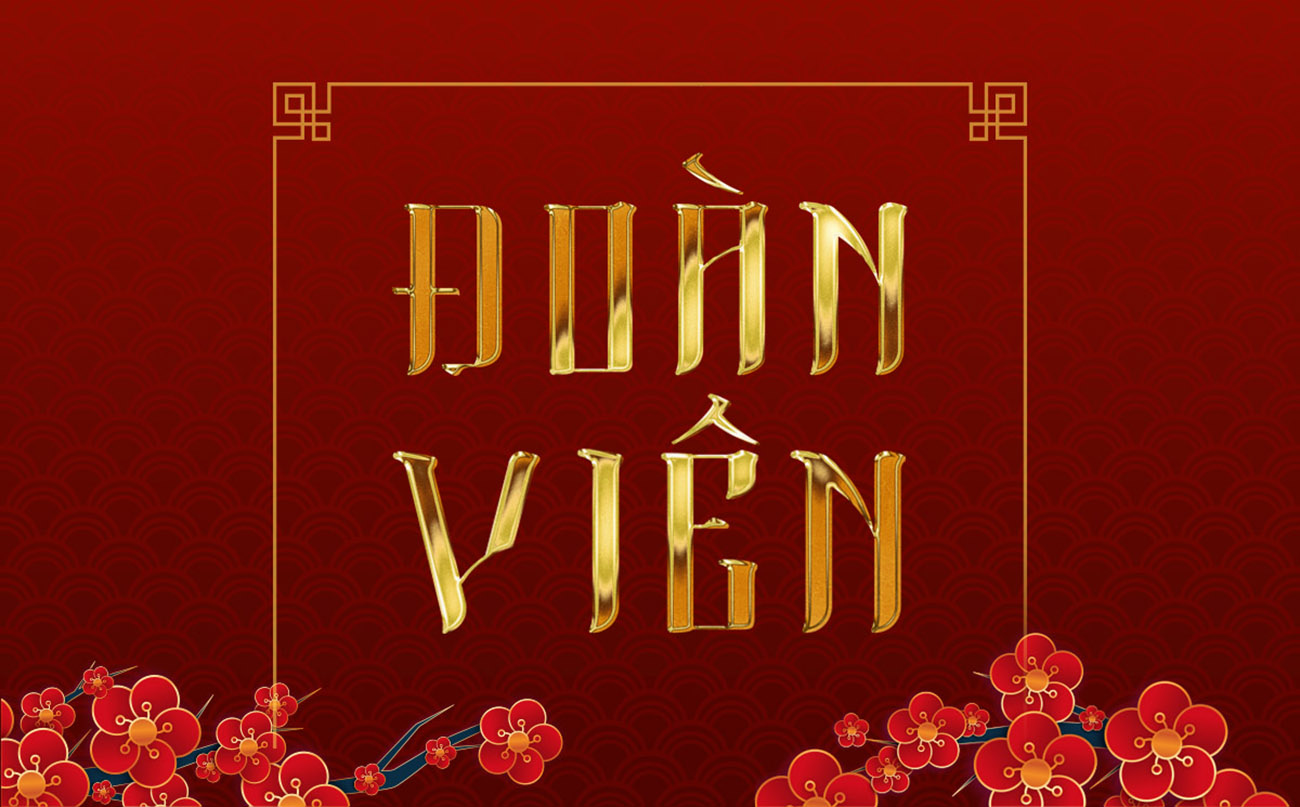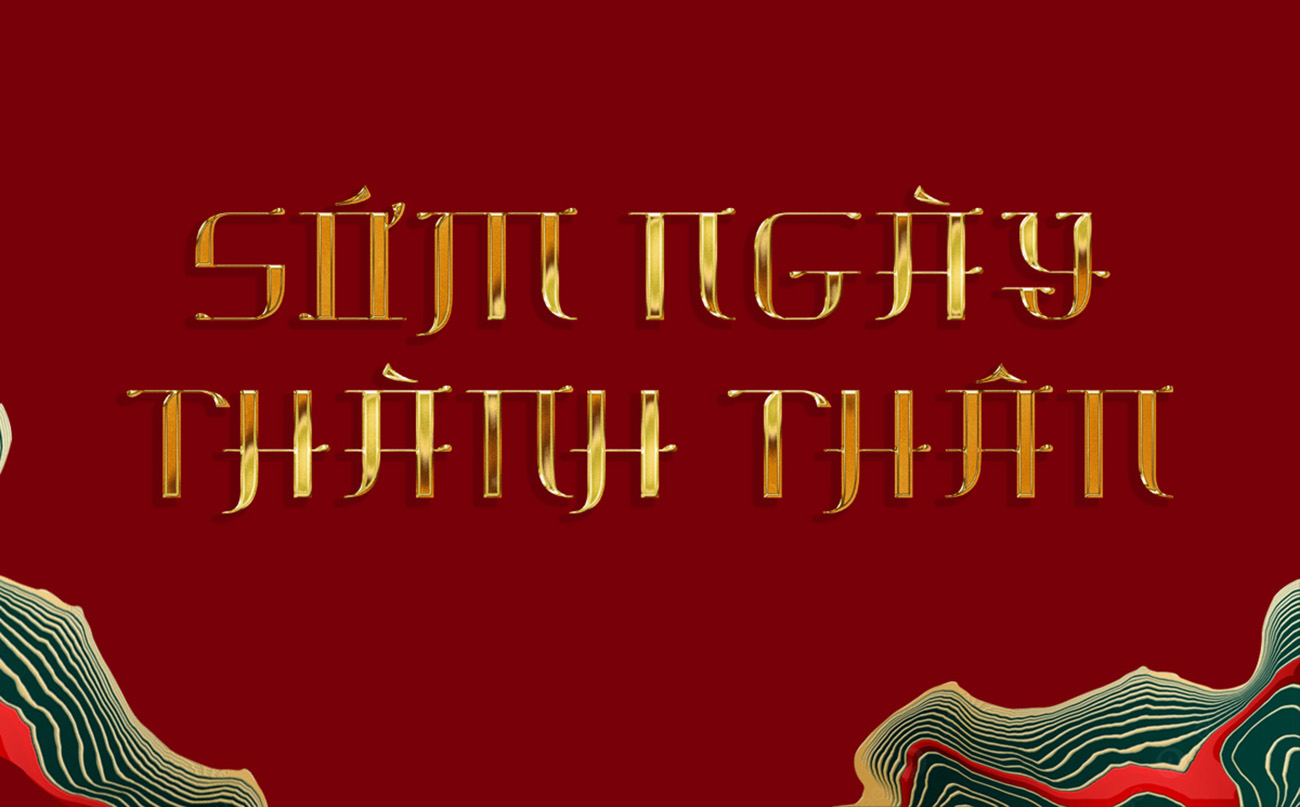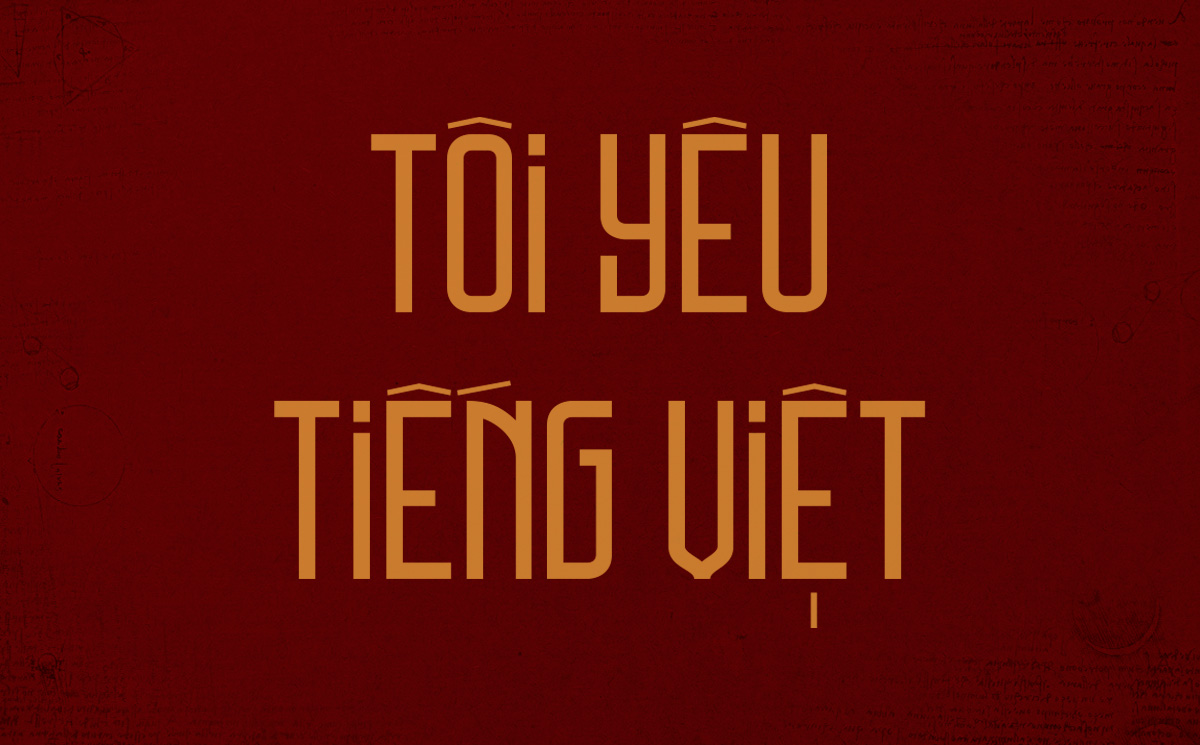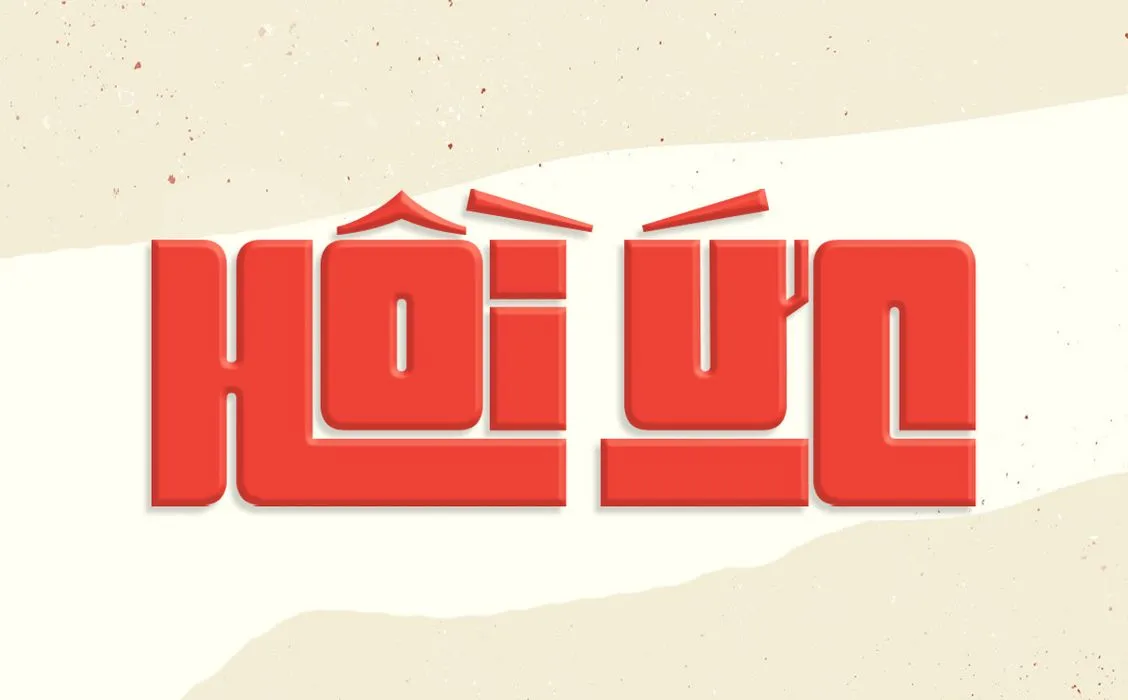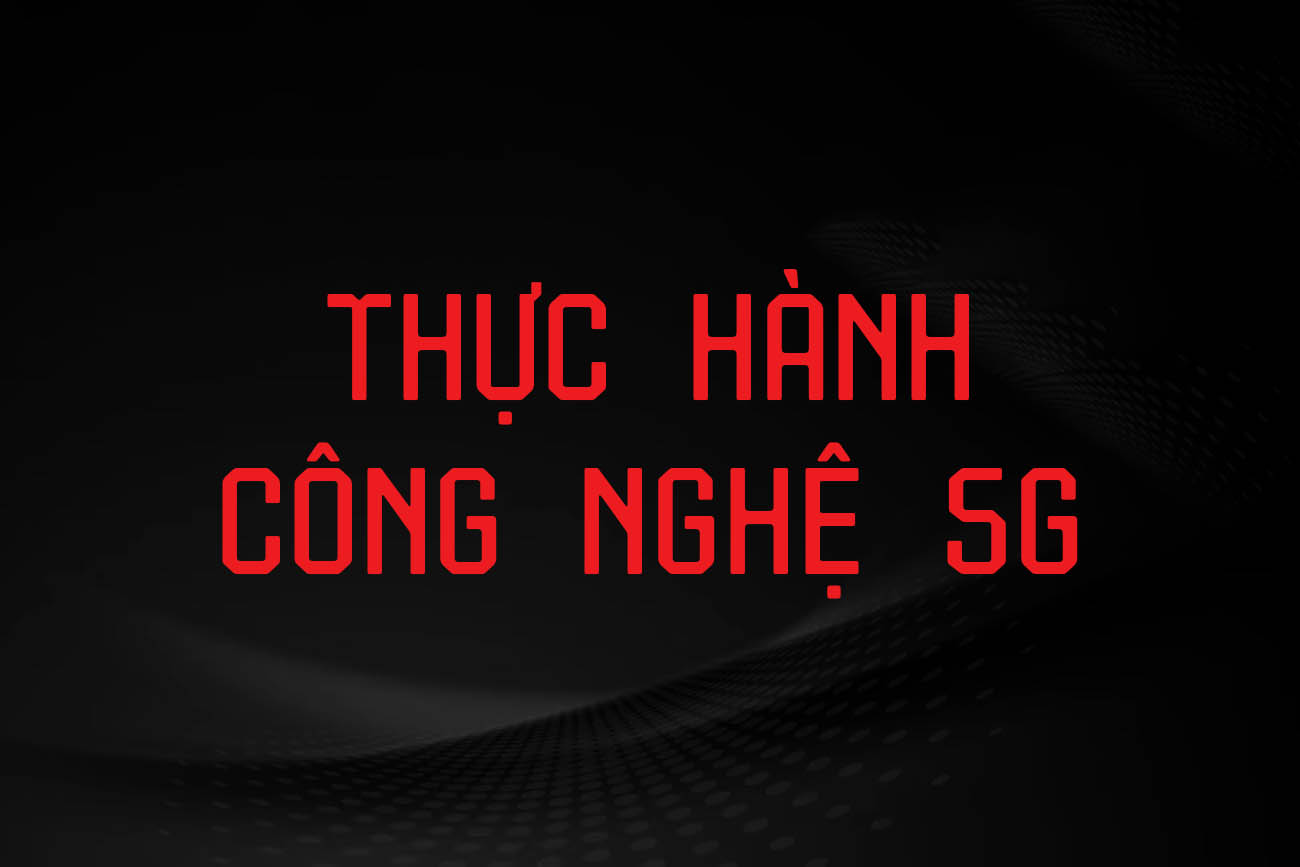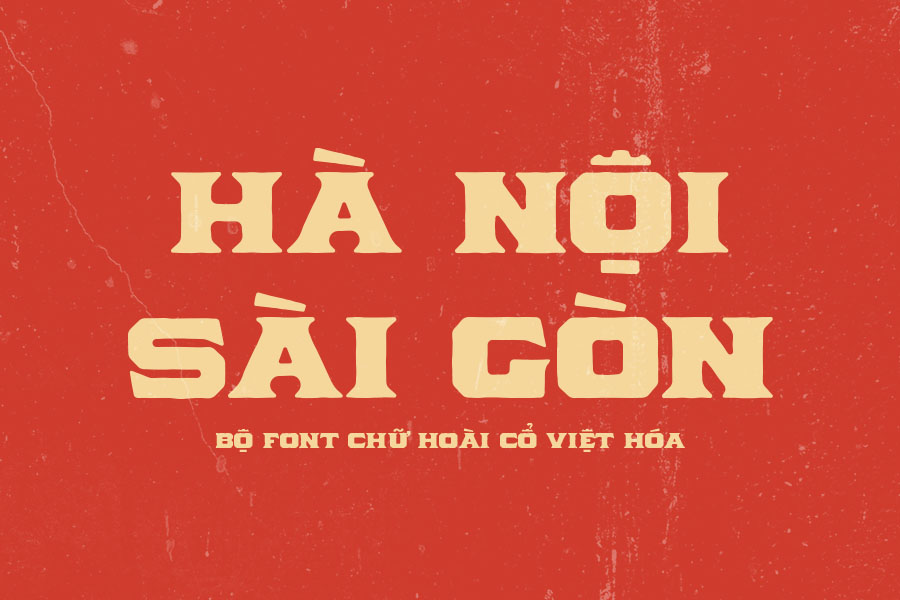
Top 12+ Font Chữ Vuông Việt Hóa Cho Thiết Kế Xưa Cũ
Khám phá bộ font chữ vuông Việt hóa đẹp nhất 2025 – vuông vức, hiện đại, rõ ràng, tải miễn phí tại Fontdep.vn.
Trong thiết kế, font chữ không chỉ đơn thuần là công cụ trình bày – mà còn là mảnh ghép văn hóa, phản ánh tinh thần của từng giai đoạn lịch sử. Ở Việt Nam, những font chữ vuông gợi nhớ biển hiệu phố xưa, áp phích cổ động hay ấn phẩm truyền thống luôn mang đến cảm giác gần gũi và đầy hoài niệm. Nếu bạn đang tìm kiếm phong cách xưa cũ, trang trọng và mang đậm dấu ấn văn hóa Việt, thì font chữ vuông chính là lựa chọn lý tưởng.
Bài viết này từ Fontdep.vn sẽ giới thiệu đến bạn bộ sưu tập font chữ vuông Việt hóa đẹp nhất 2025, mang hơi thở cổ điển, hoài niệm và gắn liền với bản sắc truyền thống.
Font chữ vuông là gì?
Font chữ vuông là kiểu chữ được thiết kế với hình dáng cân đối, gọn gàng, các nét thẳng và góc cạnh rõ ràng. Khác với những font hiện đại, font vuông mang đậm tinh thần xưa cũ và hoài cổ, thường gợi nhớ đến biển hiệu tiệm buôn, bảng quảng cáo, poster cổ động hay các ấn phẩm văn hóa từ thế kỷ trước.
Điểm đặc trưng của font vuông là sự chắc chắn, trang nghiêm và rõ ràng, tạo cảm giác bền bỉ, vững chãi – phù hợp để tái hiện không khí truyền thống, tôn vinh giá trị lịch sử và văn hóa Việt Nam. Chính nhờ đó, font chữ vuông luôn được các nhà thiết kế lựa chọn trong những dự án cần sự cổ kính, trang trọng hoặc gợi nhớ về ký ức thị giác của một thời đã qua.
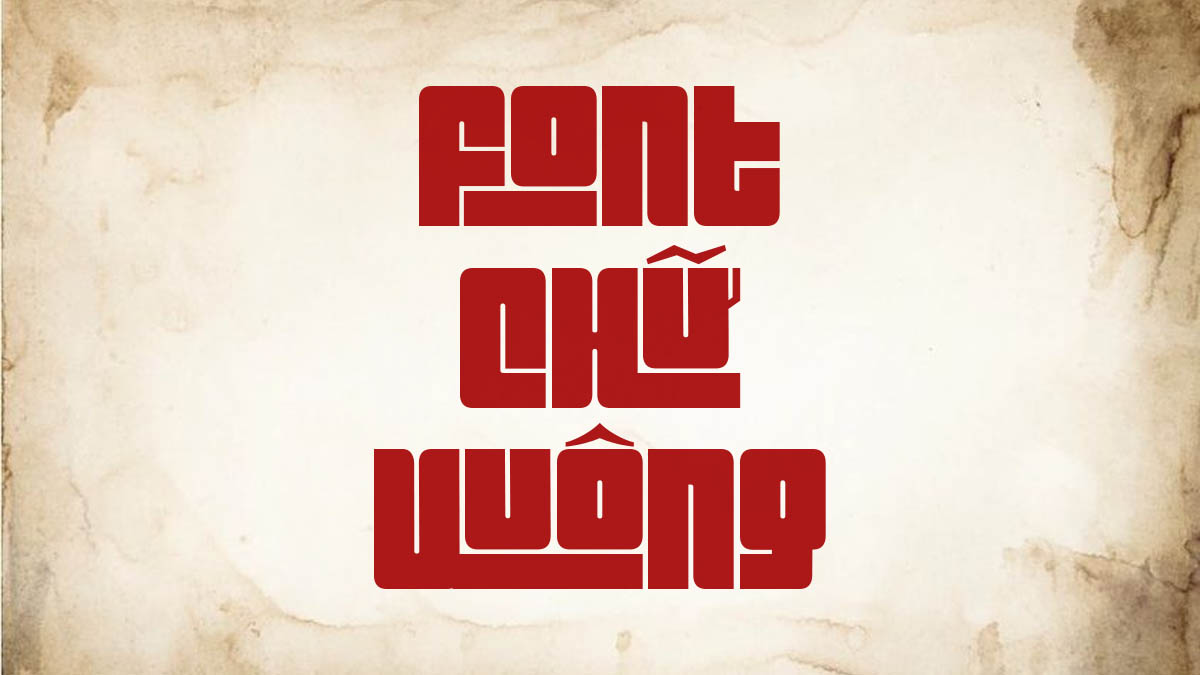
Top Font Chữ Vuông Việt Hóa Đẹp Nhất 2025
Dưới đây là những font chữ vuông vắn đẹp, đã được Việt hóa đầy đủ và rất đáng thử trong các dự án thiết kế hiện đại:
1. TH Lichsu 3 – Cổ điển, thanh mảnh
Font TH Lichsu 3 nổi bật với kiểu chữ kéo dài theo chiều dọc, thân chữ hẹp và phần đỉnh được xử lý sắc nét. Nét chữ mảnh nhưng không yếu, tạo nên phong cách truyền thống, nghiêm trang. Phù hợp với các thiết kế cần sự trang trọng, cổ kính và tính nghi lễ như poster Phật giáo, sự kiện văn hóa truyền thống.
2. TH Nhat Ban 1 – Thẳng đứng, trang nghiêm
Font TH Nhat Ban 1 gây ấn tượng bởi kiểu chữ cao và gầy, các nét dọc kéo dài tạo cảm giác trang trọng, uy nghi. Thiết kế vuông vức ở phần thân kết hợp với chi tiết bo nhẹ nơi chân chữ giúp font giữ được sự cân đối mà không bị thô cứng. Phần đầu nét chữ được xử lý sắc sảo gợi liên tưởng đến thẩm mỹ kiến trúc truyền thống Nhật Bản, khiến font trở nên rất riêng biệt, phù hợp trong thiết kế gắn với yếu tố văn hóa, nghệ thuật phương Đông hoặc cổ trang.
3. TH Degrad Mono – Cứng cáp, tối giản
Font TH Degrad Mono mang đặc trưng của kiểu chữ monospace với độ rộng ký tự đồng đều và các đường nét vuông gọn, dứt khoát. Mỗi chữ cái được thiết kế theo cấu trúc hình học đơn giản nhưng chắc chắn, tạo cảm giác mạnh mẽ và hiện đại. Dù không quá phức tạp trong chi tiết, font vẫn giữ được cá tính riêng nhờ cấu trúc thẳng đứng, phù hợp với thiết kế công nghệ, tiêu đề typography hoặc giao diện mang tính kỹ thuật số cao.
4. TH Lichsu 1 – Cổ kính, quyền uy
Font TH Lichsu 1 mang phong cách đậm chất hoàng gia với kiểu dáng chữ đứng cao, khối vuông vững chãi kết hợp chi tiết uốn lượn trang trí nơi đầu và chân chữ. Các nét kéo dài đầy đặn tạo cảm giác oai nghiêm, phù hợp với những chủ đề gắn liền với lịch sử, cung đình hoặc văn hóa cổ truyền. Kiểu chữ này thể hiện khí chất quyền lực nhưng không mất đi sự tinh xảo, giúp tổng thể thiết kế trở nên nổi bật và có chiều sâu văn hóa.
- Việt hóa bởi: Phạm Sơn - Admin S99, Fontdep.vn
5. TH China 1 – Hộp khối, phá cách
Font TH China 1 sở hữu cấu trúc cực kỳ đặc biệt với các ký tự hình khối vuông chắc nịch, kết hợp những nét cắt mạnh và góc cạnh kiểu cách tạo nên cảm giác như ký hiệu cổ trang được mã hóa. Mỗi chữ cái đều như một hình vẽ độc lập, nhưng khi ghép lại lại tạo thành tổng thể liền mạch và dễ nhận diện. Font gợi nhớ đến văn hóa phương Đông qua lối thiết kế giả lập, hiện đại mà vẫn đậm chất truyền thống, rất phù hợp cho các dự án cổ trang giả tưởng, phim hoạt hình hoặc poster game lịch sử.
- Việt hóa bởi: Phạm Sơn - Admin S99, Fontdep.vn
6. TH Hoaico 2 – Cổ điển, vững chãi
Font TH Hoaico 2 tái hiện rõ nét tinh thần thiết kế bảng biển và ấn phẩm truyền thông thời bao cấp với form chữ dày, chân to, đầu bo nhẹ tạo cảm giác cũ kỹ nhưng vẫn dễ nhìn. Các ký tự mang tỷ lệ vuông gần chuẩn, nét cắt khỏe khoắn, tạo nên sự chắc chắn và mạnh mẽ trong thị giác. Dù mang đậm phong cách retro Việt Nam, font vẫn rất linh hoạt khi áp dụng vào thiết kế hoài niệm như poster phim xưa, bìa sách lịch sử hoặc các dự án tôn vinh văn hóa đô thị cổ.
- Việt hóa bởi: Phạm Sơn - Admin S99, Fontdep.vn
Font chữ vuông không chỉ là lựa chọn thẩm mỹ trong thiết kế, mà còn là nhịp cầu nối liền quá khứ và hiện tại. Những nét chữ vuông vắn, trang nghiêm, gợi nhớ biển hiệu, áp phích hay ấn phẩm xưa cũ chính là cách để chúng ta tái hiện lại bầu không khí văn hóa truyền thống Việt Nam.
Nếu bạn mong muốn mang sự hoài niệm, cổ kính và bản sắc dân tộc vào trong các thiết kế, thì bộ sưu tập font chữ vuông Việt hóa trên chắc chắn sẽ là nguồn tài nguyên đáng giá.